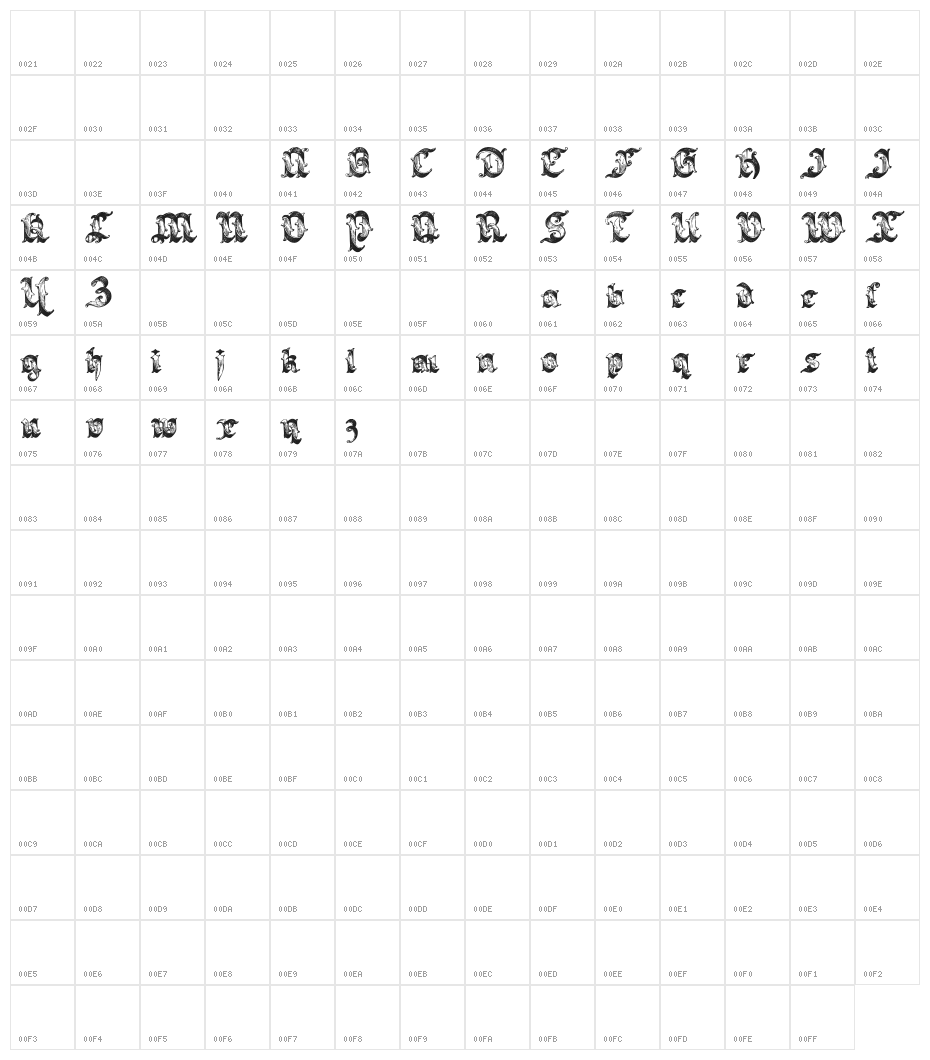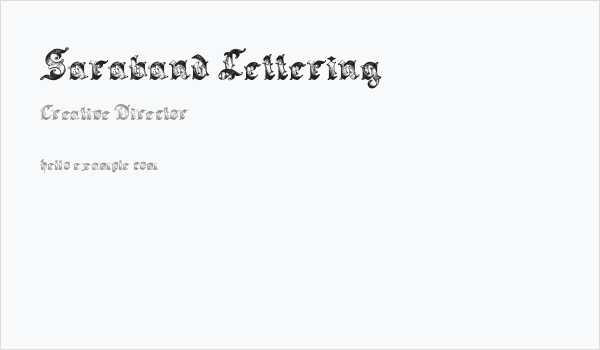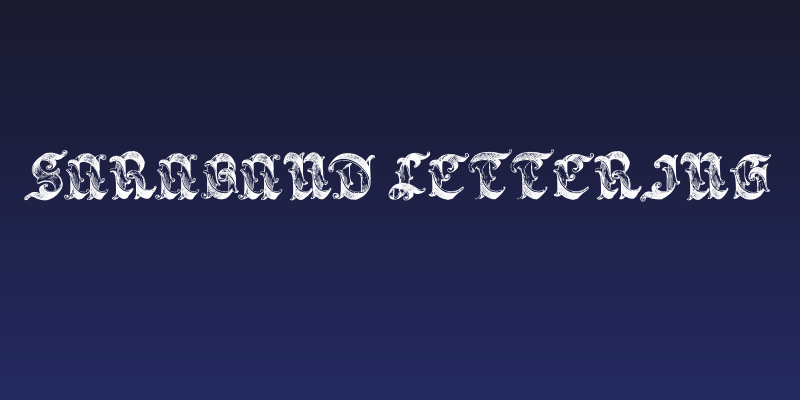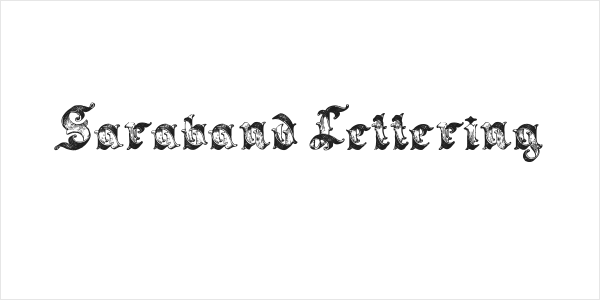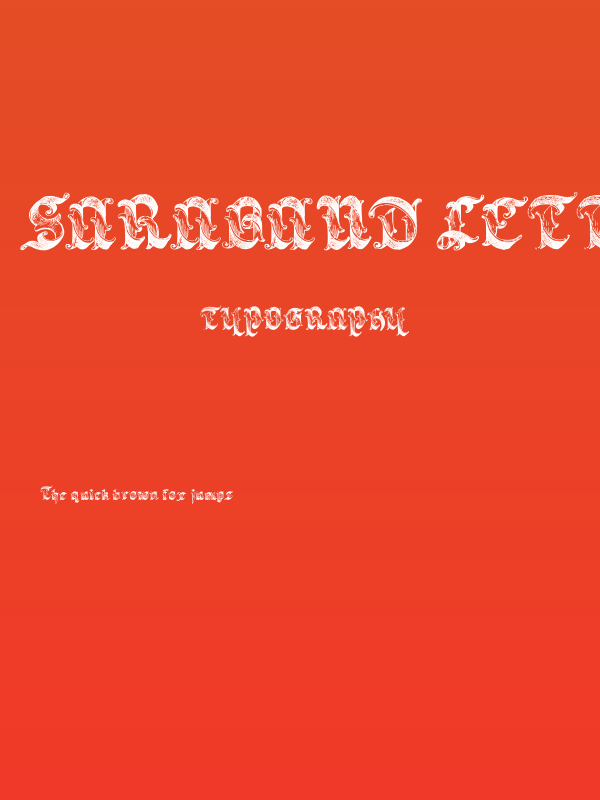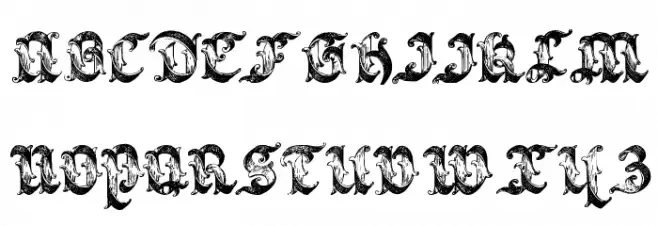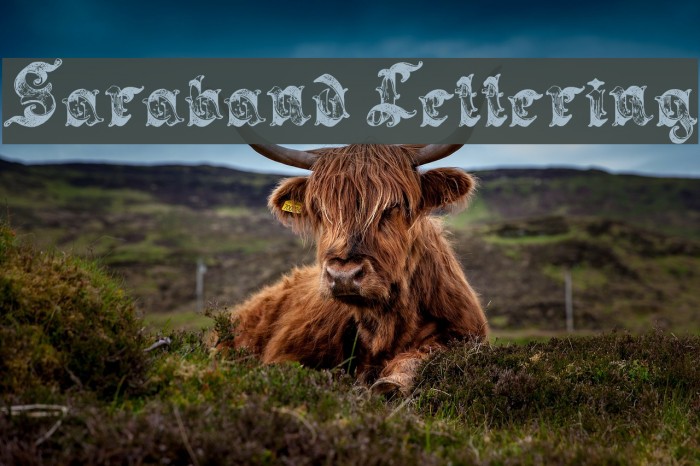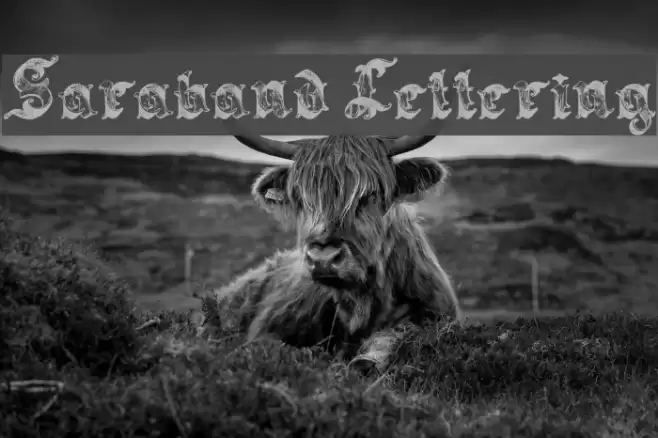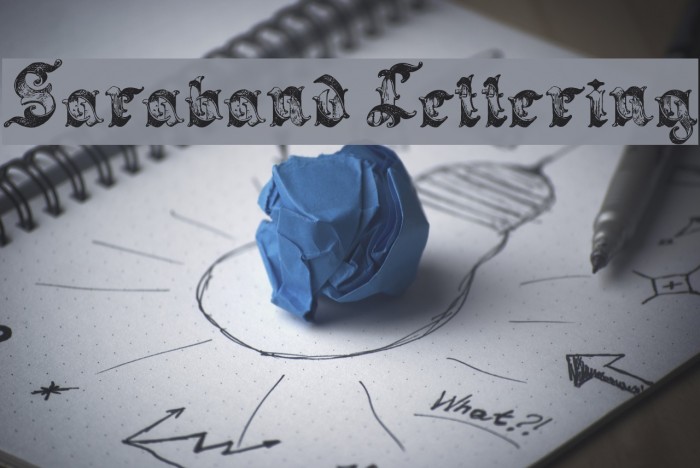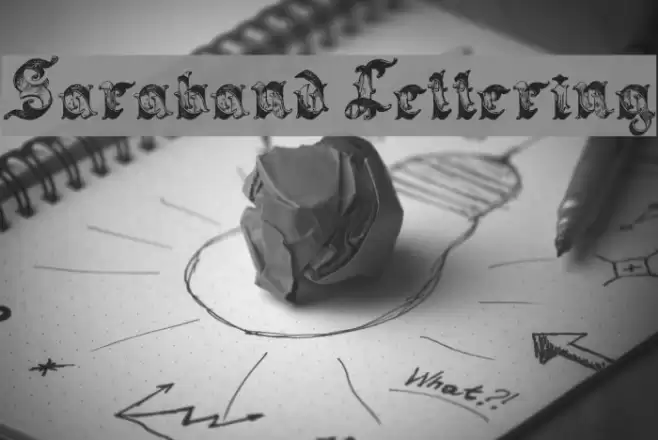
Saraband Lettering Font
✎ Gothic
| Kategorien | Gothic |
| Anwendungsfall | Logos, Headlines, Decorative text |
| Vorgeschlagene Projekte | Ideal for wedding invitations, historical themed events, book covers, and decorative signage. |